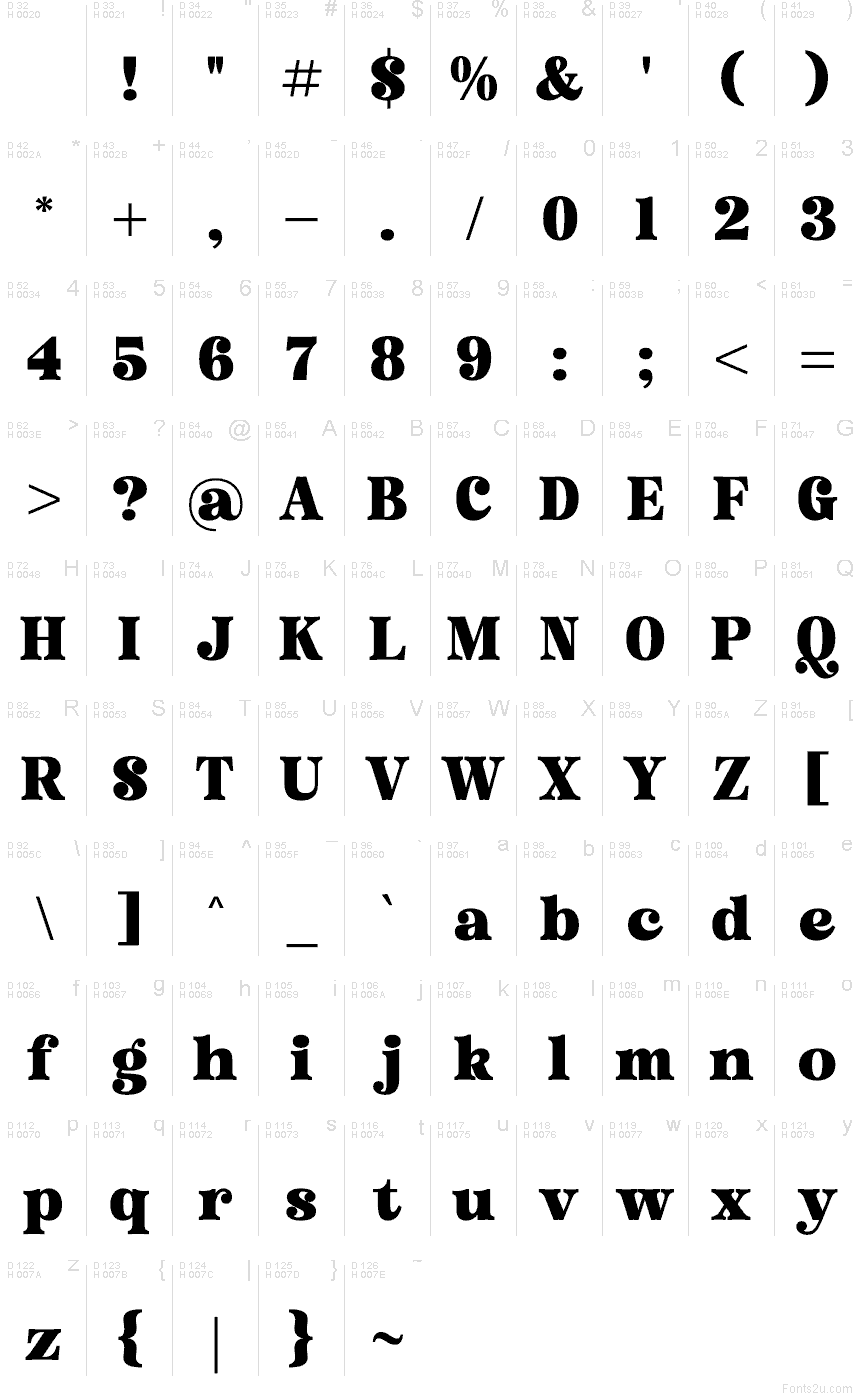
Trendy Voyage, da TimelessType.co, é uma fonte serifada retrô gratuita com a suavidade característica da estética editorial dos anos 70. As letras apostam em formas robustas e de alto contraste, com serifas levemente alargadas, enquanto as junções arredondadas mantêm um tom descontraído e nada formal. É elegante, sem ser rígida.
Esta fonte gratuita é perfeita para branding de moda, embalagens de beleza, capas de revistas, menus de cafés e títulos onde se deseja um toque vintage sem parecer rústico. Também funciona muito bem para títulos curtos e monogramas, pois as curvas amplas e as pontas das serifas garantem uma presença marcante, digna de um pôster, mesmo com poucas letras.